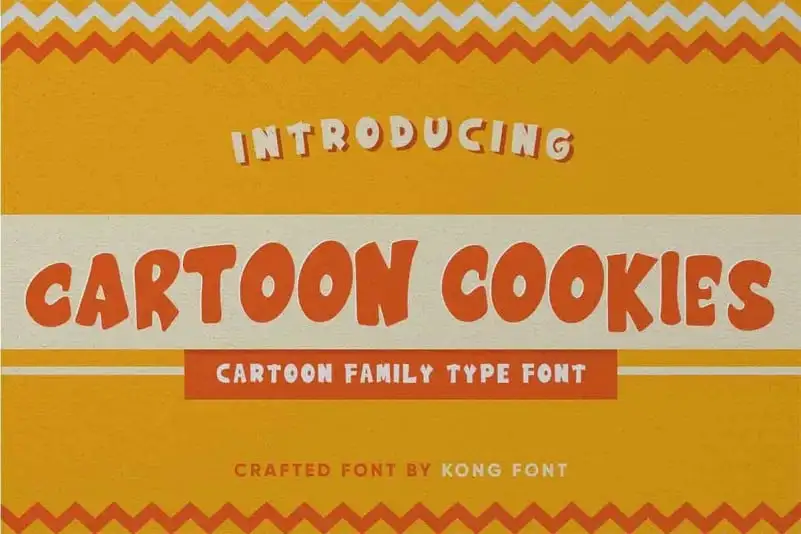
Cartoon Cookies Display Font – Download Grátis
Aproveite a oportunidade de adquirir Cartoon Cookies Display Font, uma opção perfeita para qualquer projeto que precise de uma face de texto para imprimir ou digitalizar. Esta fonte de exibição é um tipo leve e colorido, repleto de vida e encanto. Ela destaca-se pelo seu ar moderno e divertido, criado especialmente para aqueles momentos em que você deseja algo prático e divertido. Ideal tanto para cartões como para livros infantis ou frases memoráveis, a Cartoon Cookies Display Font também se destaca quando usada na promoção, embalagens, logomarcas, arte e qualquer outra coisa inusitada. Sem dúvida, ela traz uma pitada de leveza e amabilidade ao seu design, tornando-a um recurso visual indispensável para quem busca um tipo que chama atenção sem perder a sua simplicidade e encanto.